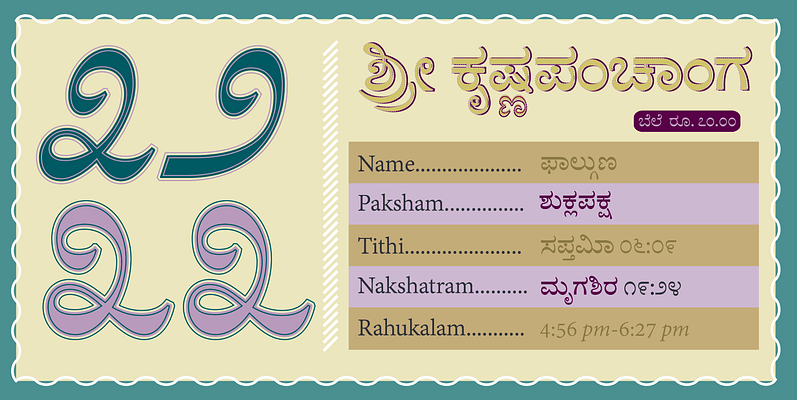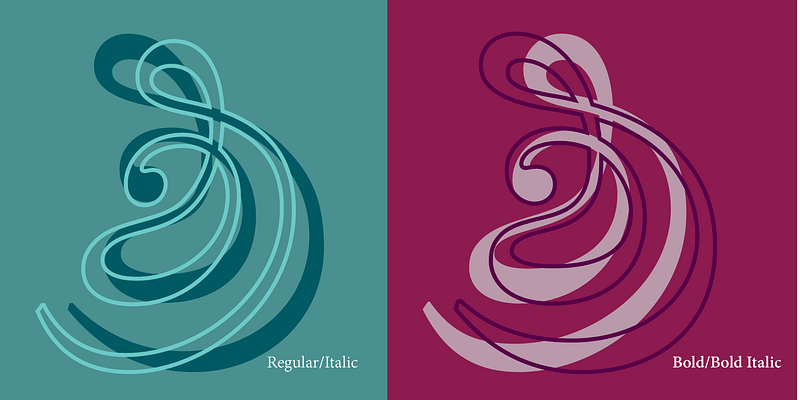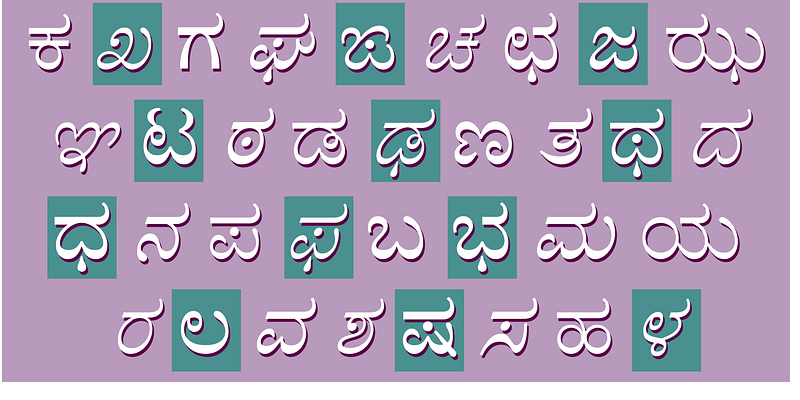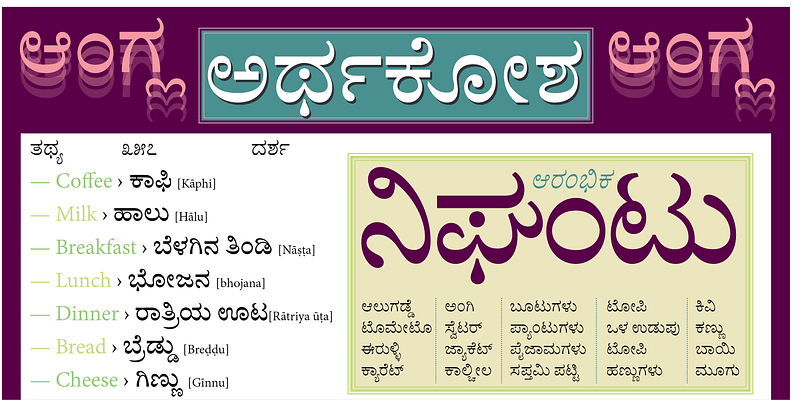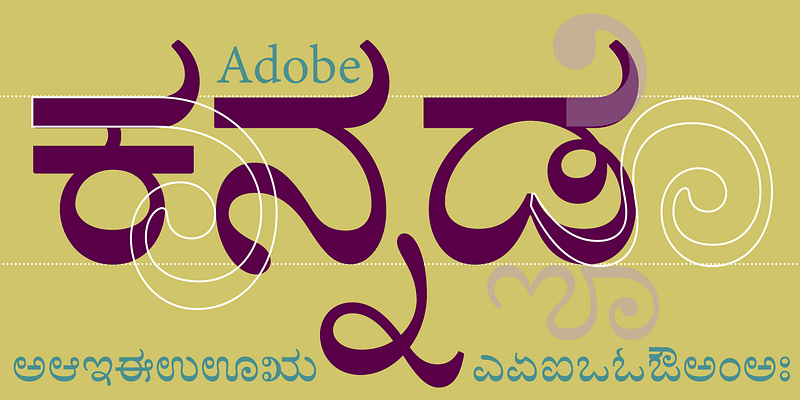
「Adobe Kannada」書体のデザインは、Erin McLaughlin が担当し、ブラフミック文字の専門家である Fiona Ross が監修しました。この書体ファミリーは、見た目のサイズとスタイルの両面が、アドビの他のブラフミックフォントと調和するようにデザインされており、この書体ファミリー群が 1 つのシステムとして一緒に組版できるようになっています。印刷物、特に連続した文字の組版に重点が置かれ、それを目指してデザインを行いました。
文字の構造は、伝統的なカンナダ語のテキスト書体をベースにしており、その中には、後続のカンナダ語の書体デザインにおいて、ウエイト、字形、プロポーションの強力な先例となっている、強力な影響力を持つ Basel Mission Press Kannada 書体も含まれています。Adobe Kannada は、小さなサイズでも力強く誤読の少ない形を維持するために、コントラスト配分を通常よりもやや低くしています。また、シェイプやディテールにも細心の注意が払われており、小さなテキストから見出しやディスプレイサイズまで、様々な書体サイズで使用できます。
「Adobe Kannada」フォントは、Unicode 規格の文字エンコードに準拠しており、OpenType® レイアウトを利用して、正しいスクリプト形状を実現しています。カンナダ語の合字のフルセットがフォントに含まれており、カンナダ語のテキストを自然に表現できます。またすべての母音記号と修飾文字のカーニングが慎重に配置されています。このフォントには、カンナダ語のプロポーショナル数字が含まれています。